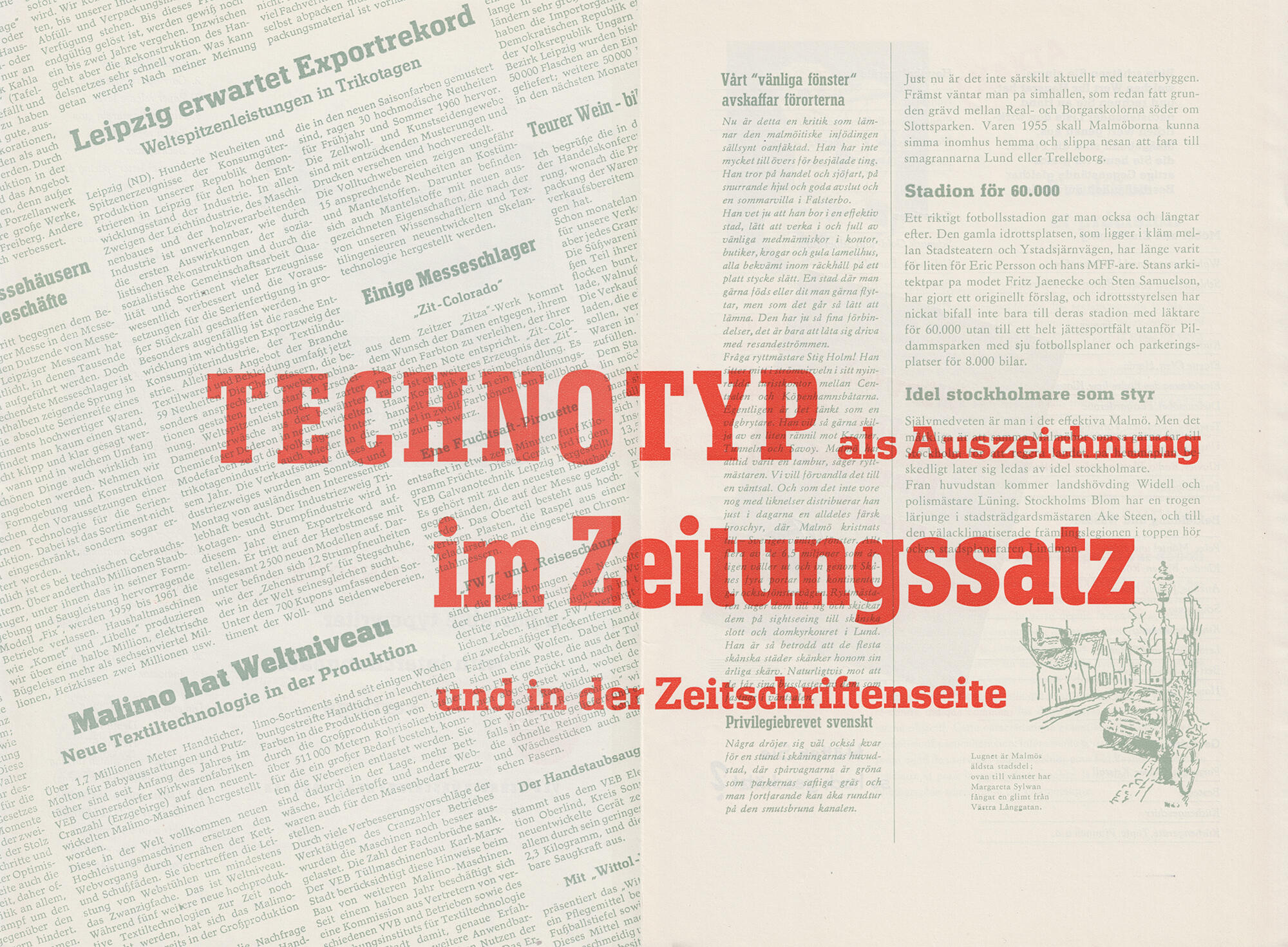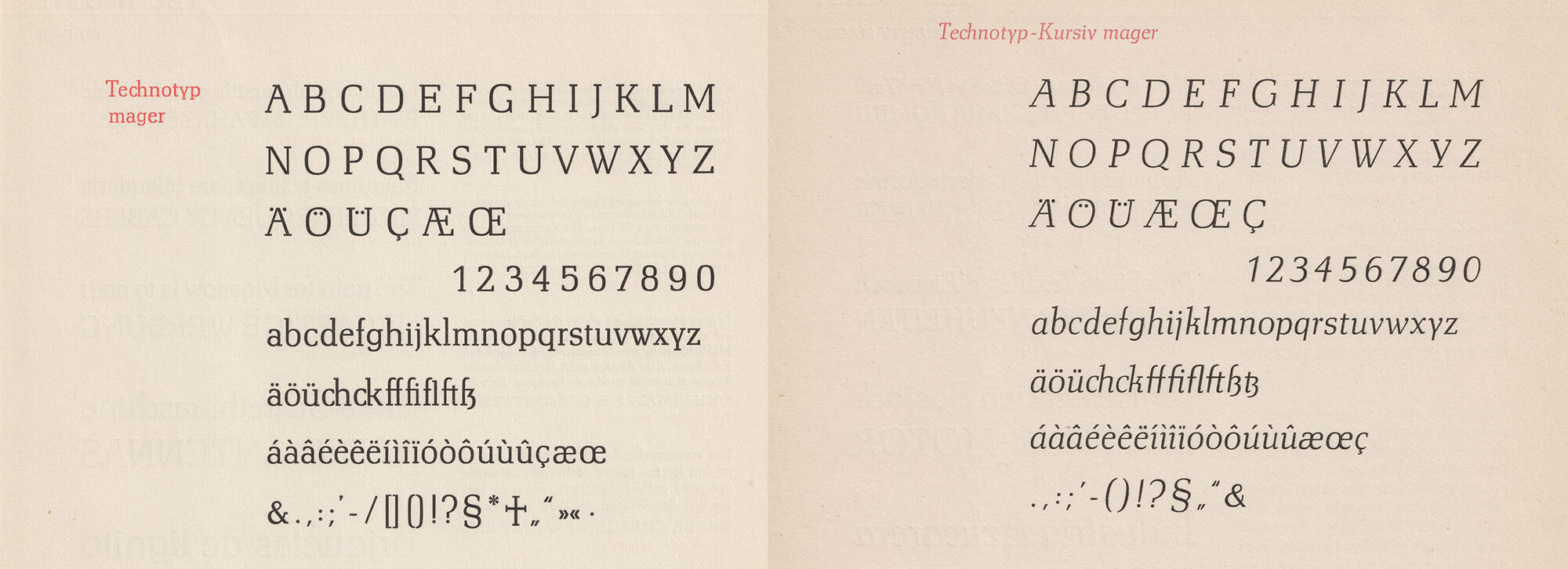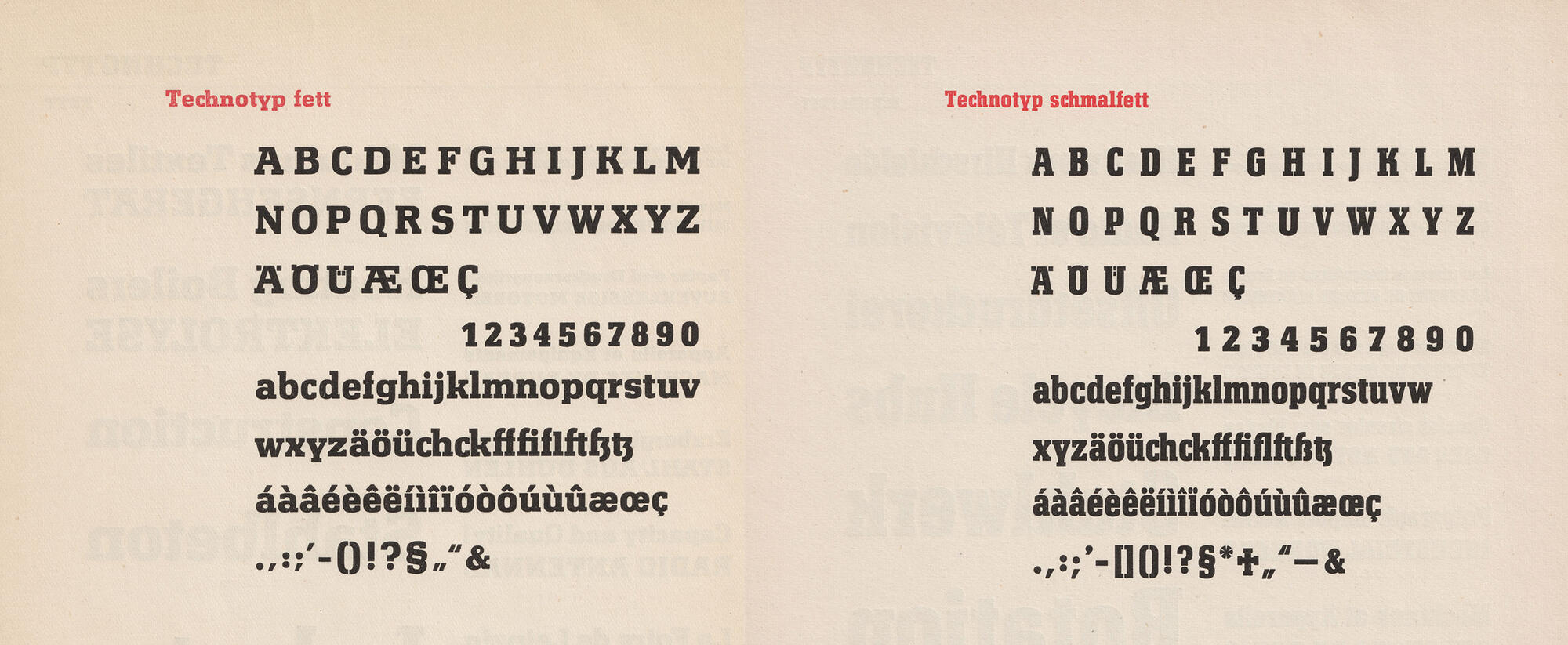
Die Technotyp von Herbert Thannhaeuser erschien ab 1948 zunächst bei der Leipziger Schriftgießerei Schelter & Giesecke und später im Volkseigenen Betrieb Typoart.
Digitalisierungen:
• Technotyp von Coen Hofmann (2011) über URW++ in 11 Schnitten
• Eurotech Pro von Ralph M. Unger (2011) über sein Label RMU Fonts mit kyrillischem Sprachausbau